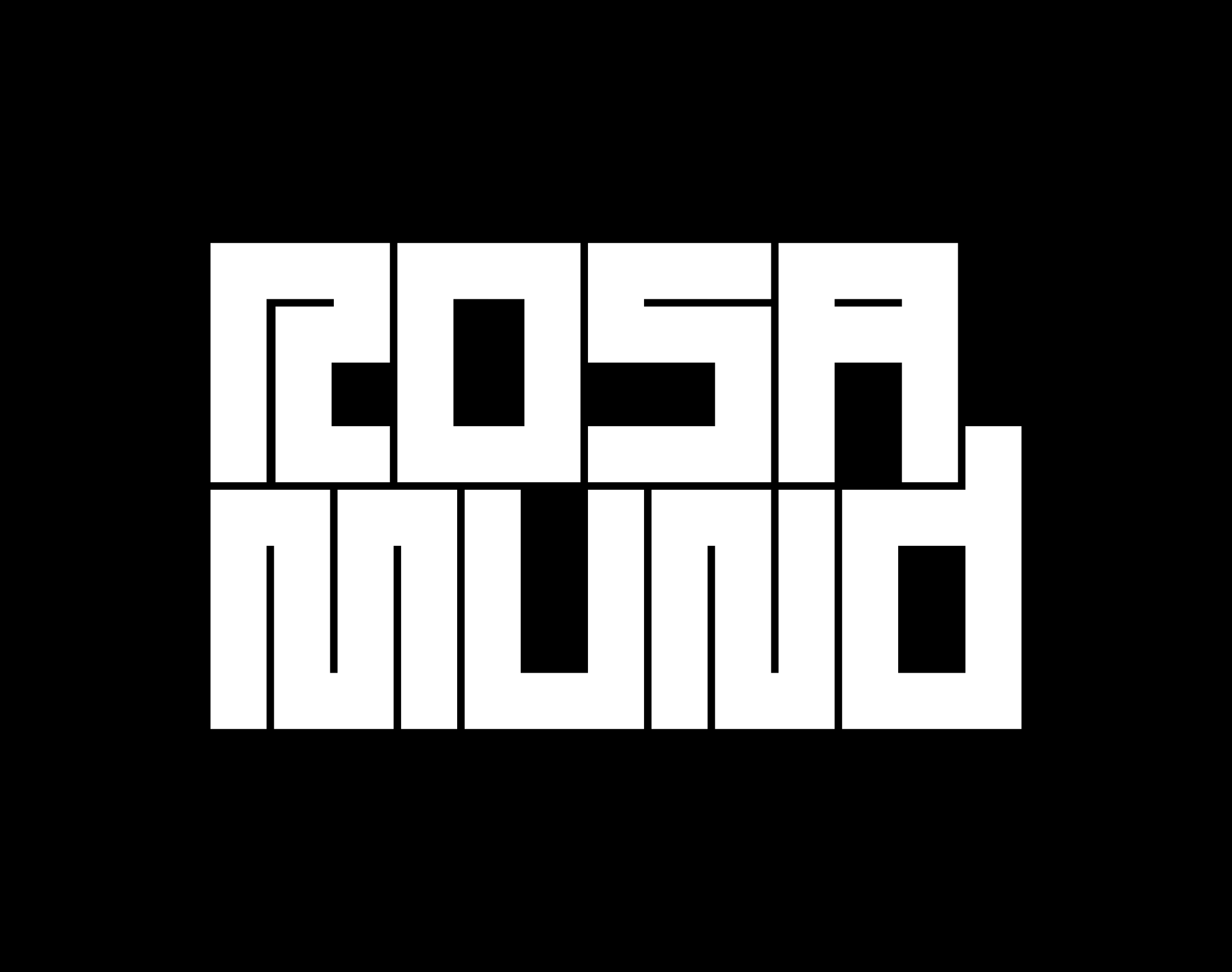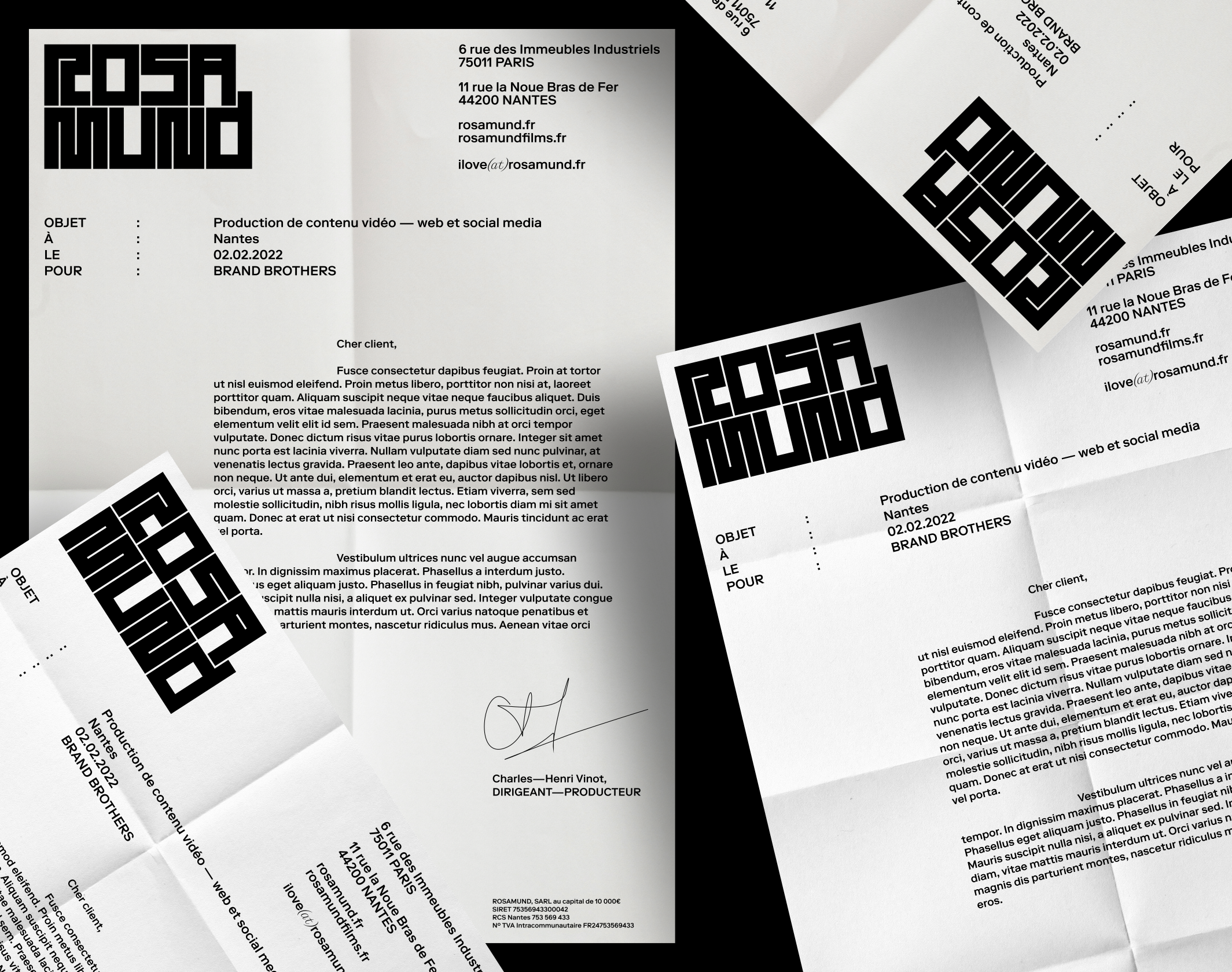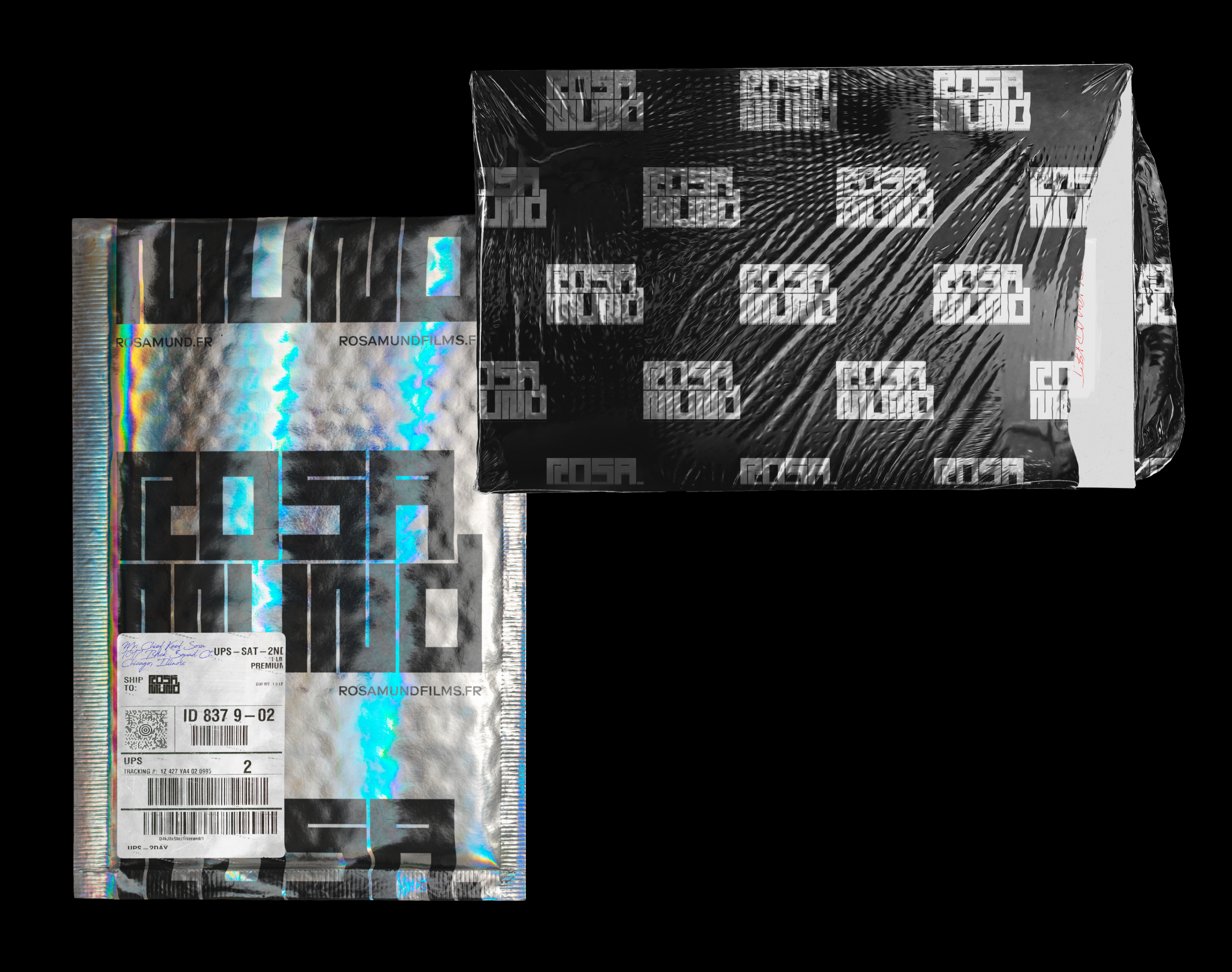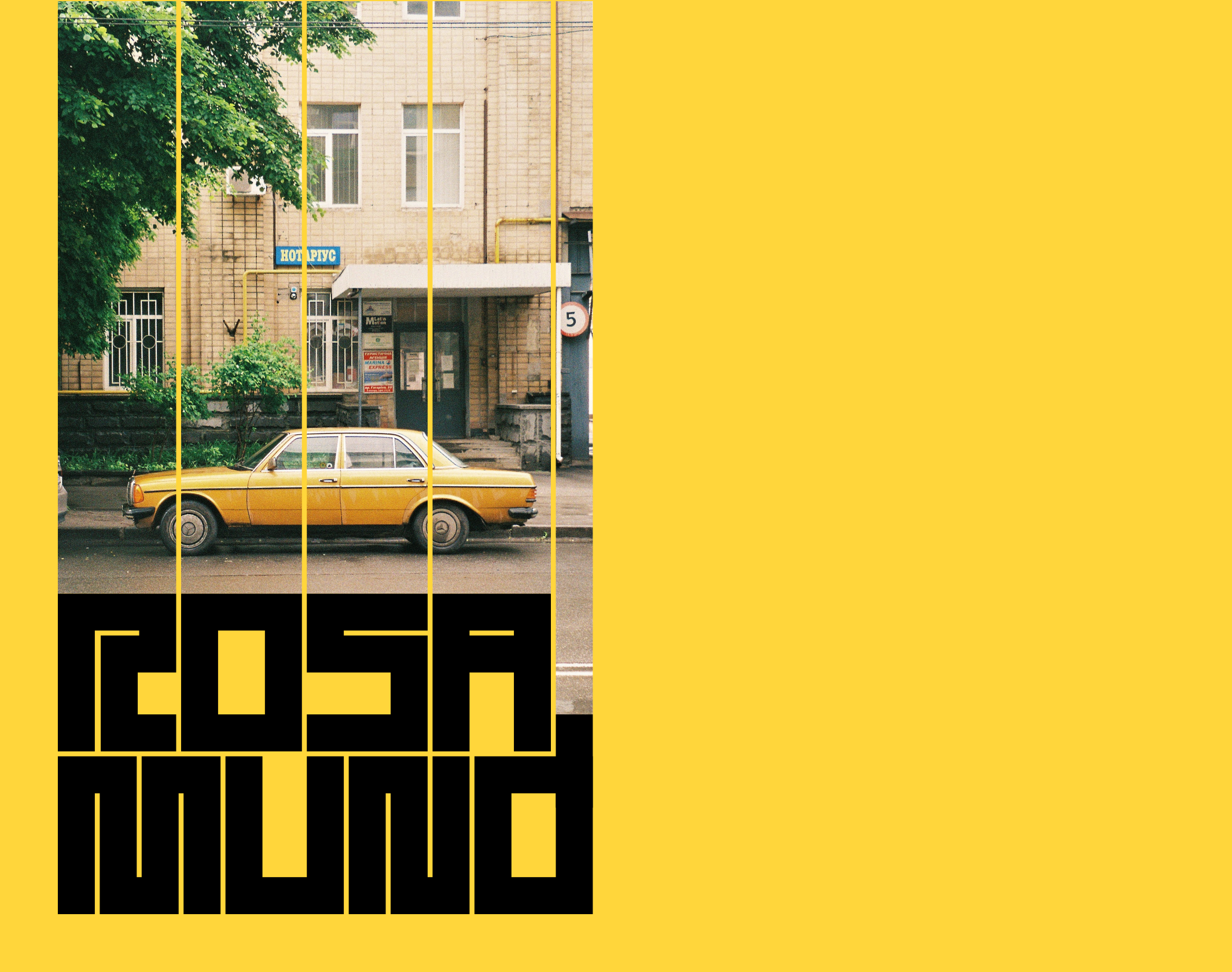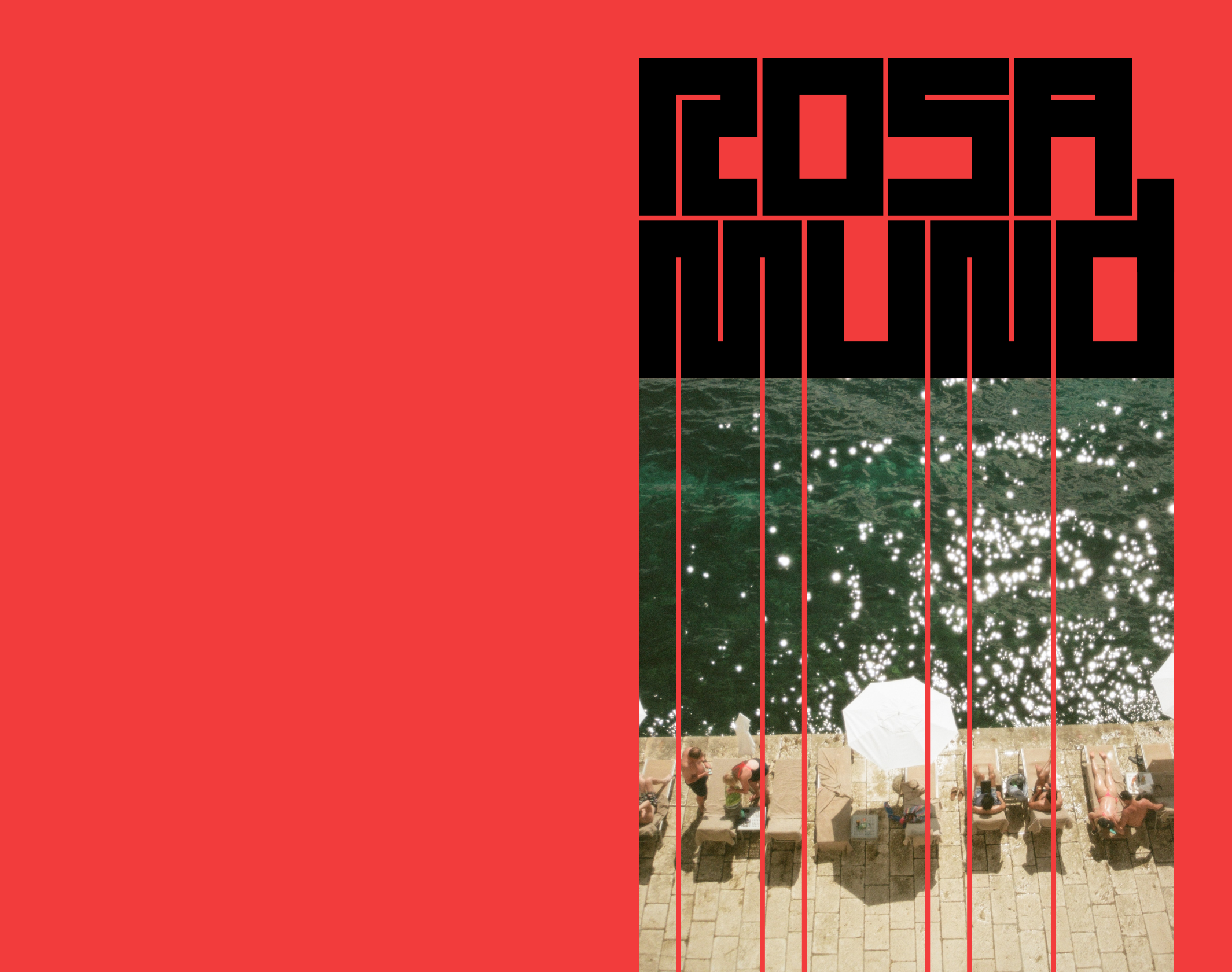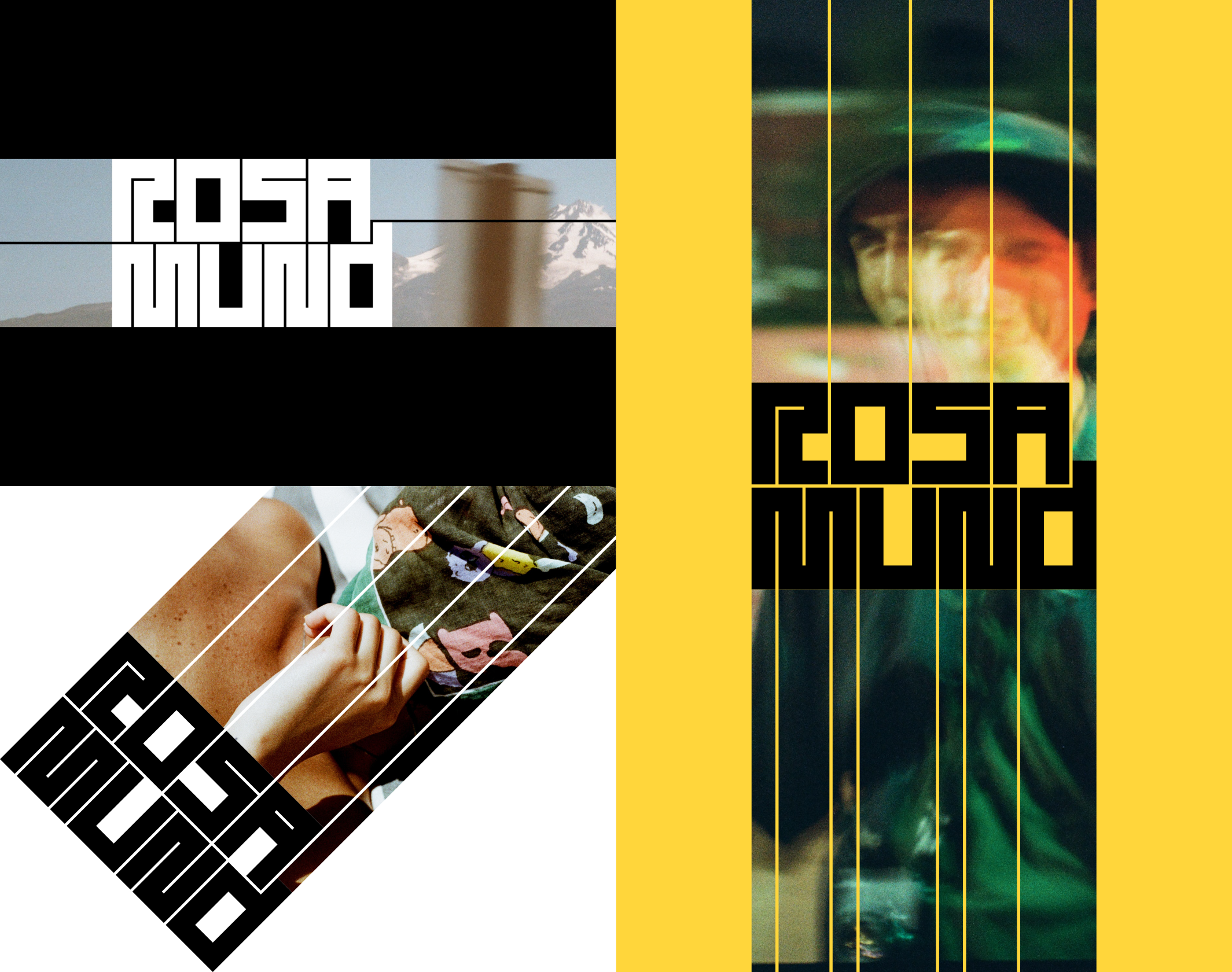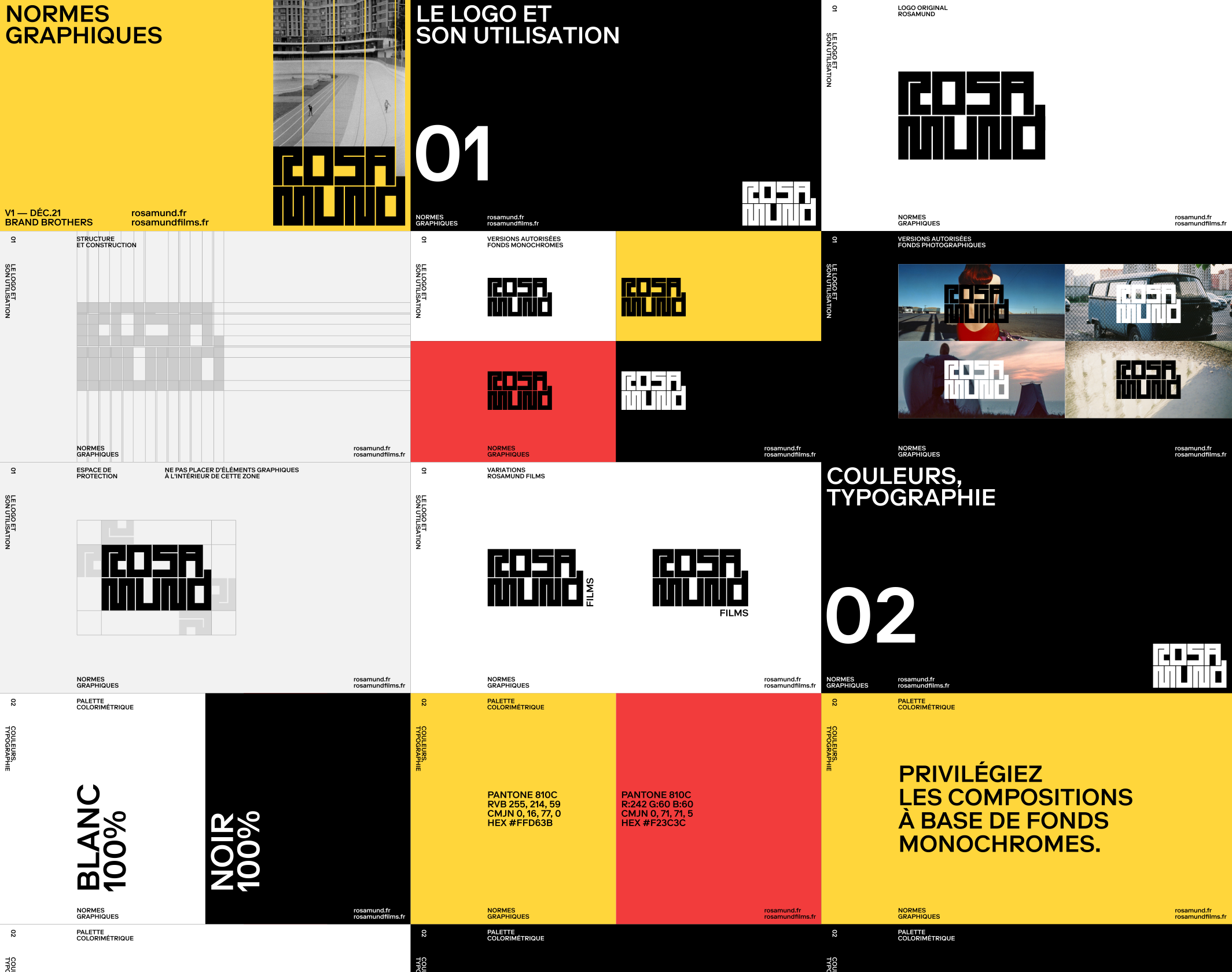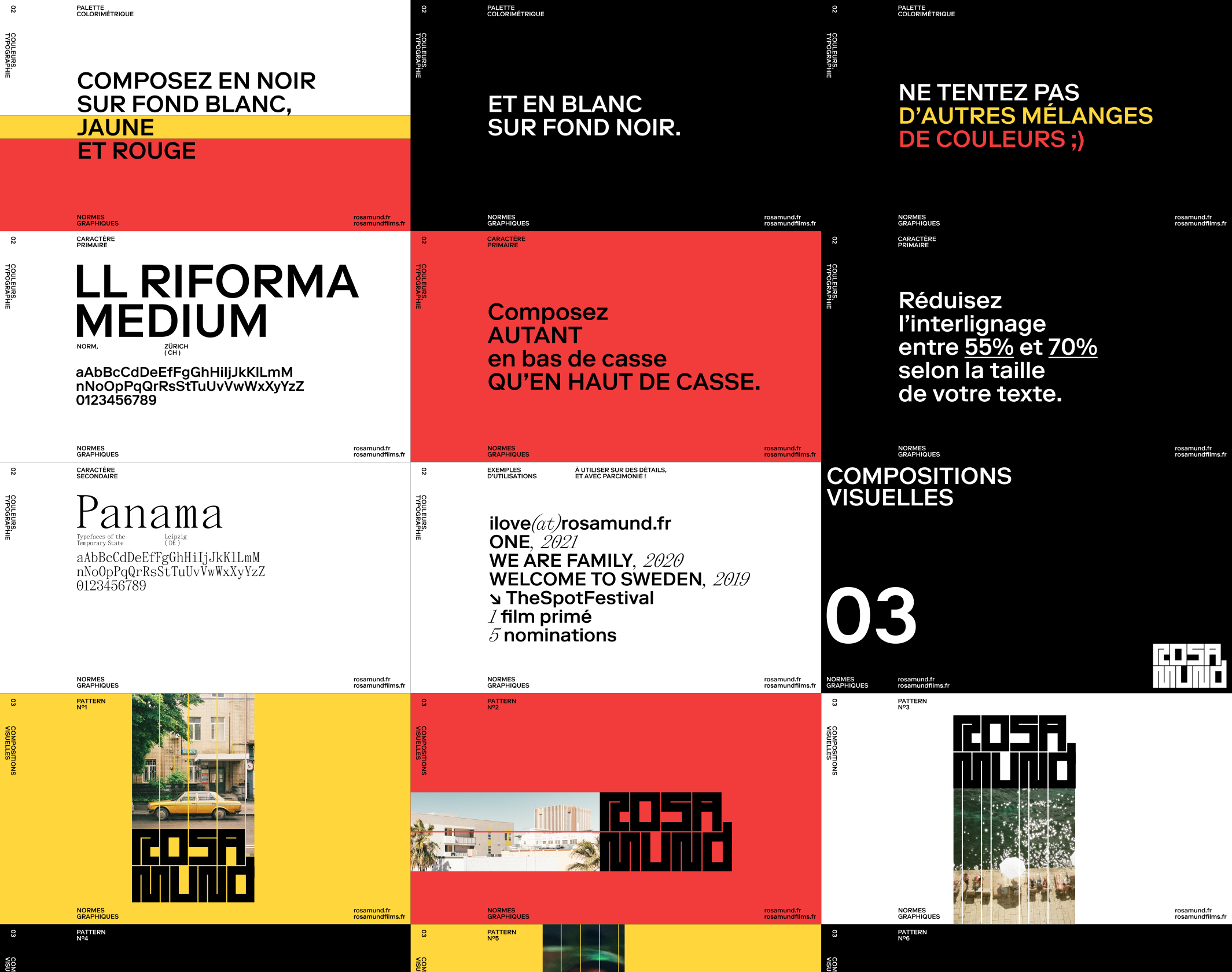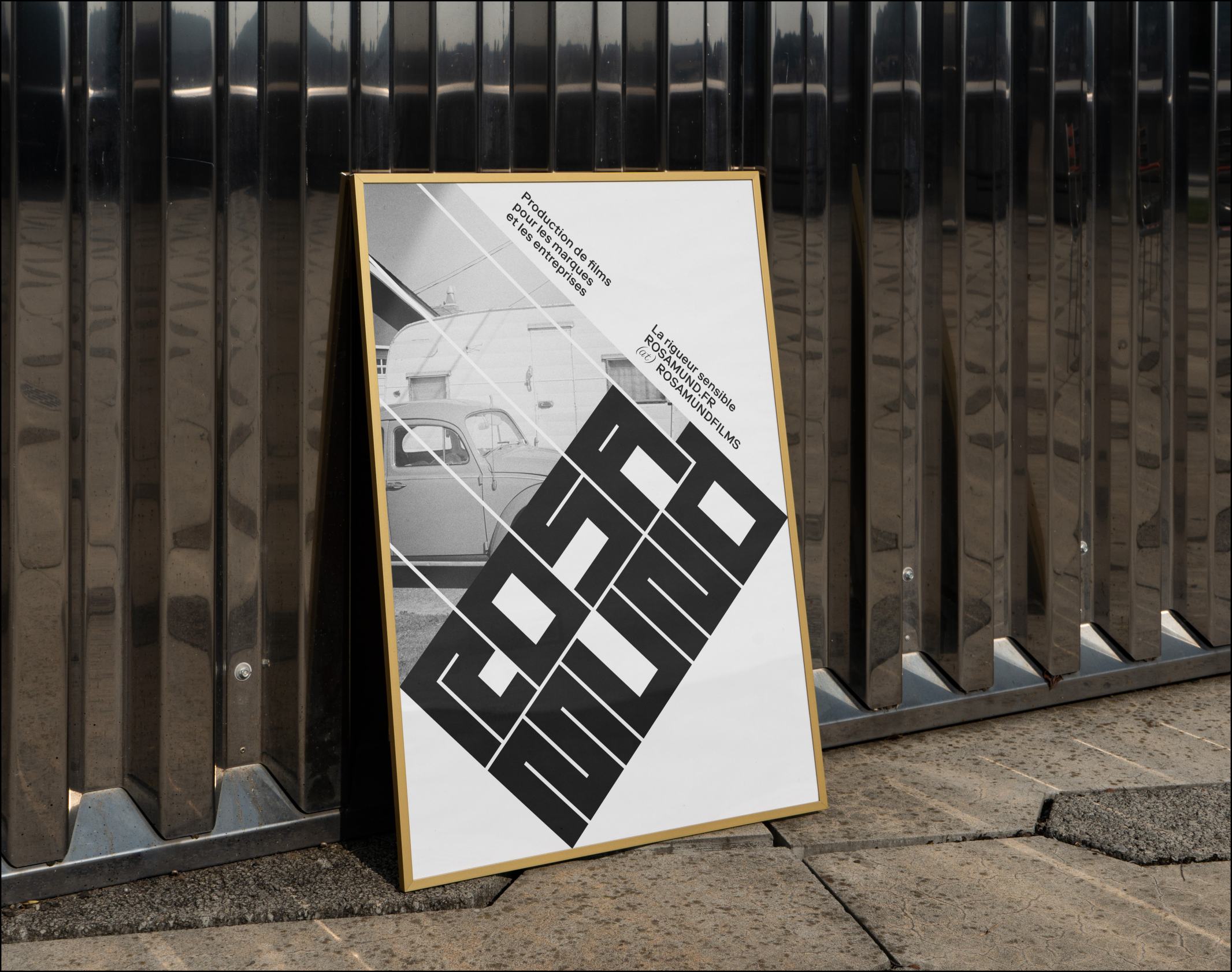
Rosamund
Rosamund, l'agence de production vidéo, réinvente son identité graphique pour refléter son équilibre entre rigueur et sensibilité créative.
Rosamund est une agence de production de contenus vidéo pour les marques et les entreprises, basée à Nantes et Paris depuis 2012. Travaillant avec de nombreux groupes français sur de nombreux formats de films d’entreprises et développant depuis peu un pôle films et fiction, l’agence a décidé d’accompagner son changement de nom – de Linkit à Rosamund – d’une refonte complète de son identité graphique avec Brand Brothers.
Définissant son travail d’image comme rigoureux et sensible à la fois, Rosamund met en avant des histoires vraies, tournées comme des documentaires, dopées par une exigence technique et créative reconnue. Cet équilibre est traduit dans l’identité par un typogramme épais et structuré, dégageant des notions de puissance et d’exactitude ; la marque typographique dialogue directement avec l’image par un système de fenêtres modulaires, qui permet d’exprimer la force et la variété du contenu produit par l’agence. Ce procédé de composition offre aux équipes des possibilités de renouvellement permanent quand à la présentation du travail de Rosamund, sur des formats physiques ou digitaux. L’ensemble du territoire visuel, à la fois dépouillé et intense, est flanqué du caractère LL Riforma (Norm, Zurich), édité par Lineto.